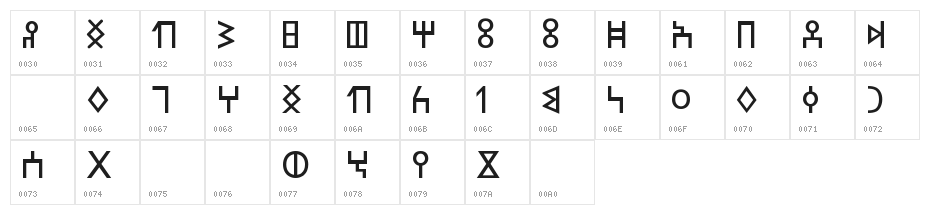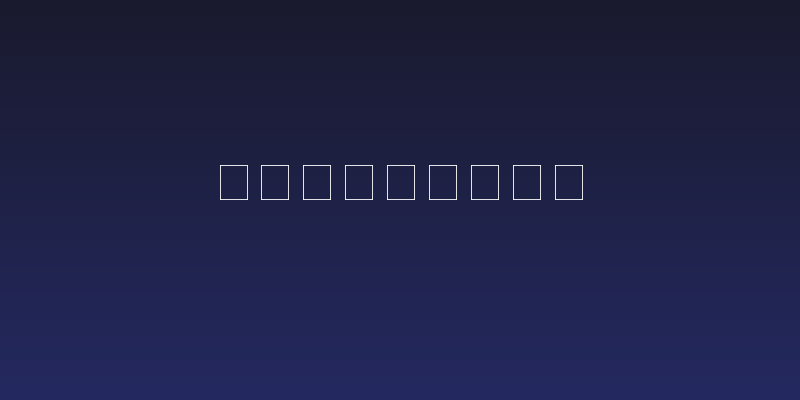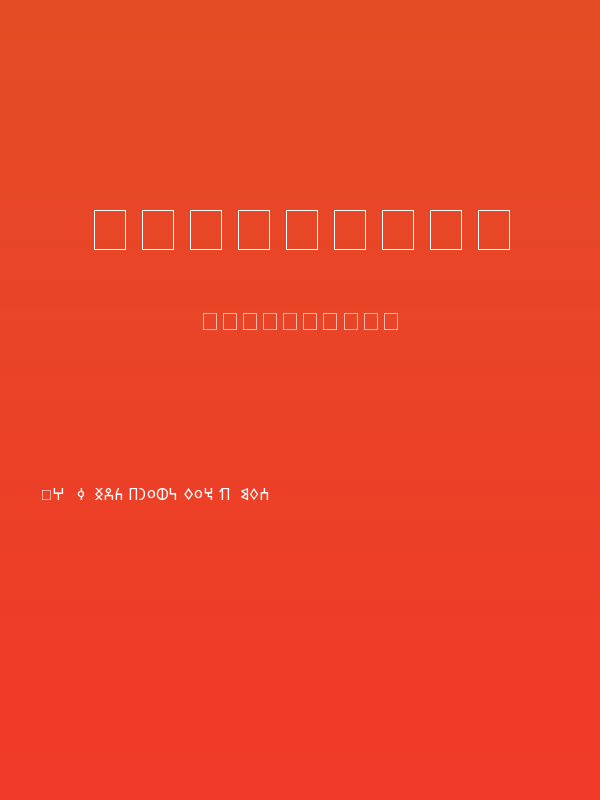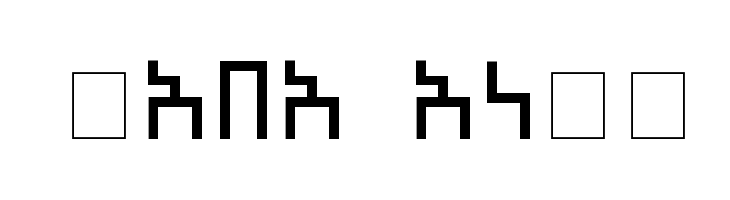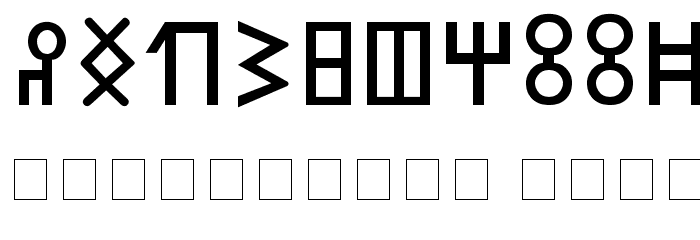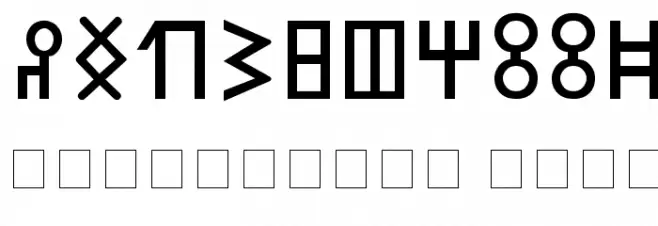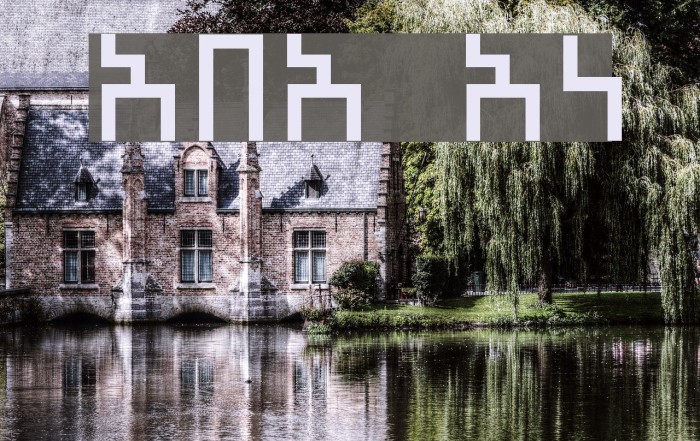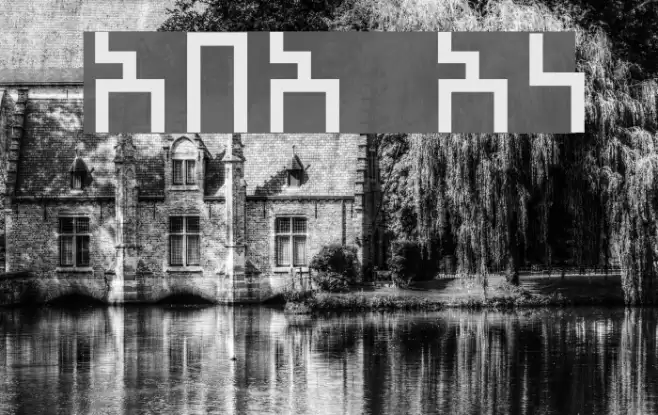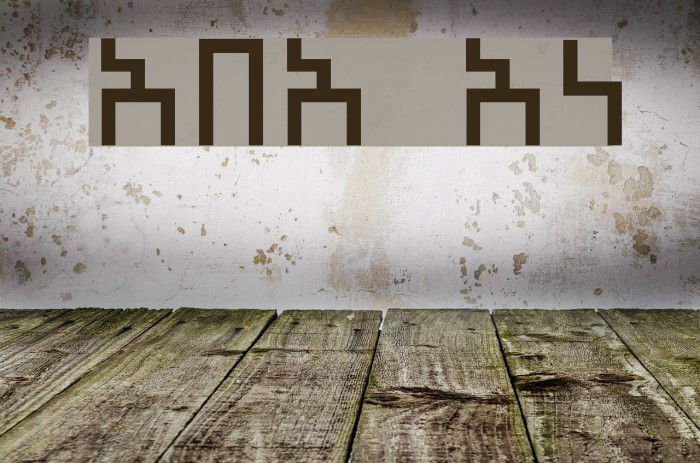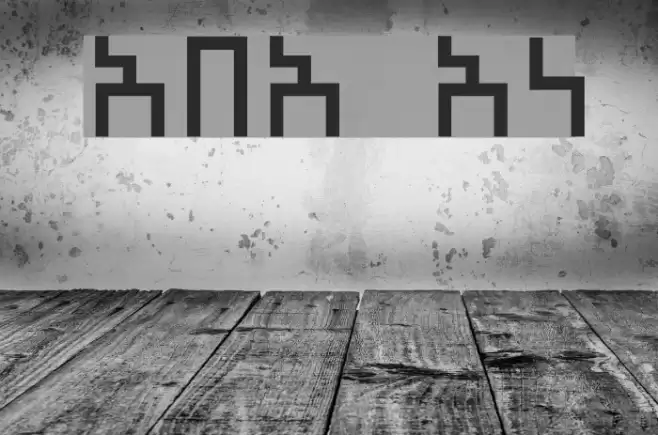
SabaeanGG Font
✎ Dingbats
| Nume | SabaeanGG |
| Categorii | Dingbats |
| Stil general | Historical, Symbolic |
| Caz de utilizare | Cultural displays, Historical documentation |
| Proiecte propuse | This script could be used for historical research, cultural studies, or artistic projects that require ancient or symbolic scripts. |